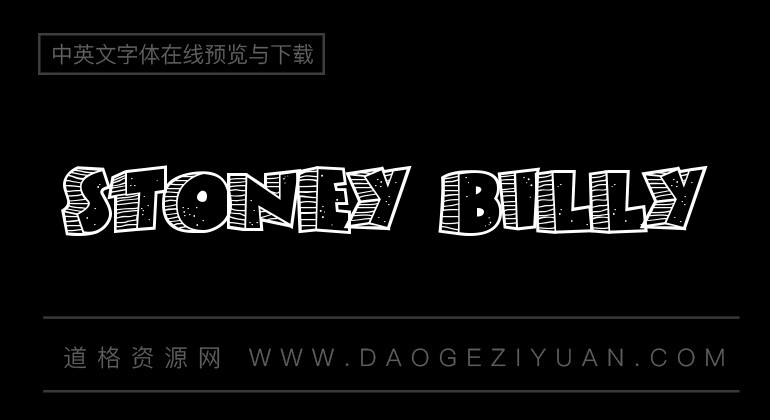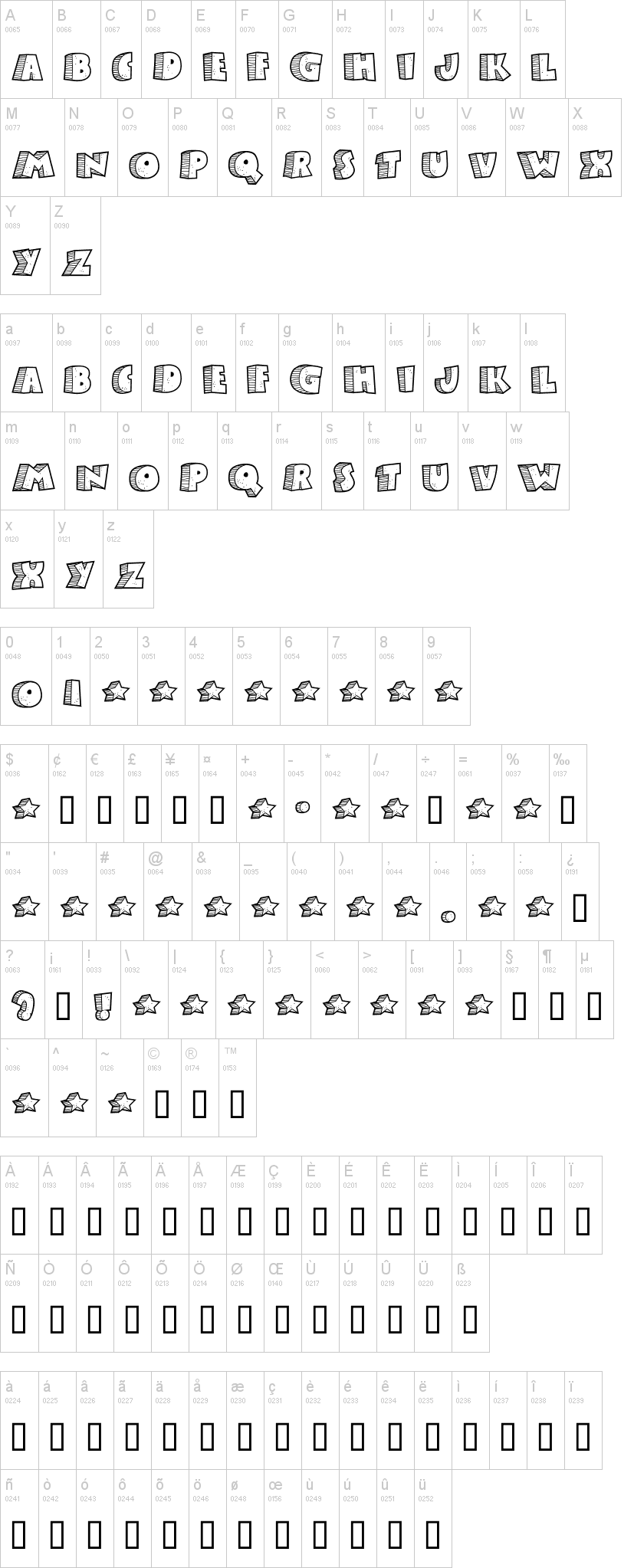
Stoney Billy
Stoney Billy 是由古典英式风格设计师James T. Edmondson设计的一款现代英文字体。它具有极具特色的粗细轮廓,充满活力,适合用于多种不同的设计项目,如海报、标志、标题等。它的特点是拥有英式古典风格的粗细轮廓,每个字母都有一定的美感,而且它的字母组合也很漂亮,可以为设计师的作品增添更多的美感。
Stoney Billy是一款非常不错的手写艺术字体,具有很好的视觉感,适合于文化类的宣传设计、商业类品牌的广告和产品包装设计以及个性化文字排版等较多场景。